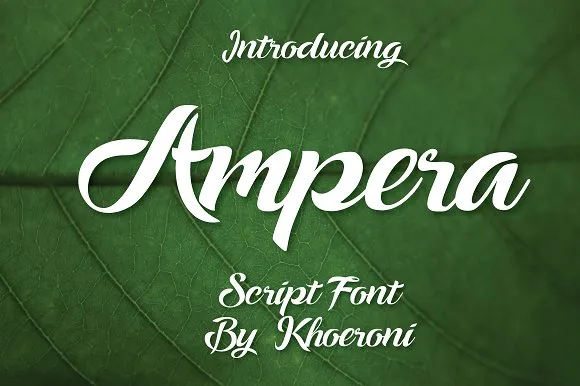
Ampera Script Font – Fonte Grátis
Ampera Script Font
Introduzimos a você uma nova adição à nossa biblioteca de fontes: Ampera Script Font, criada por menangan studio. Este é um tipo tipográfico script, intenso e vibrante, que transmite energia única com suas linhas curvas delicadas. Ideal para diversas aplicações gráficas, a fonte Ampera Script pode ser usada tanto em logotipos quanto nas embalagens de produtos; também se adequa perfeitamente a posters, cartões-postais, convites casamentos e até mesmo na moda, como adesivos e camisetas. Com sua personalidade singular e elegante, Ampera Script é um recurso indispensável para quem busca dar vida à uma marca ou produto através de seu design visual distintivo. Ampera Script não apenas pode estilizar a forma tradicional de mensagens escritas à mão, mas também oferece os benefícios da facilidade na tipografia digital. Ideal tanto para designers gráficos quanto para aqueles que buscam criar um elemento único e encantador em qualquer projeto visual.